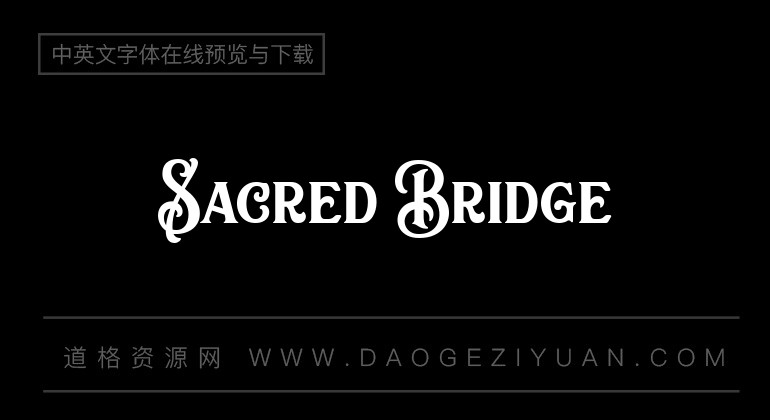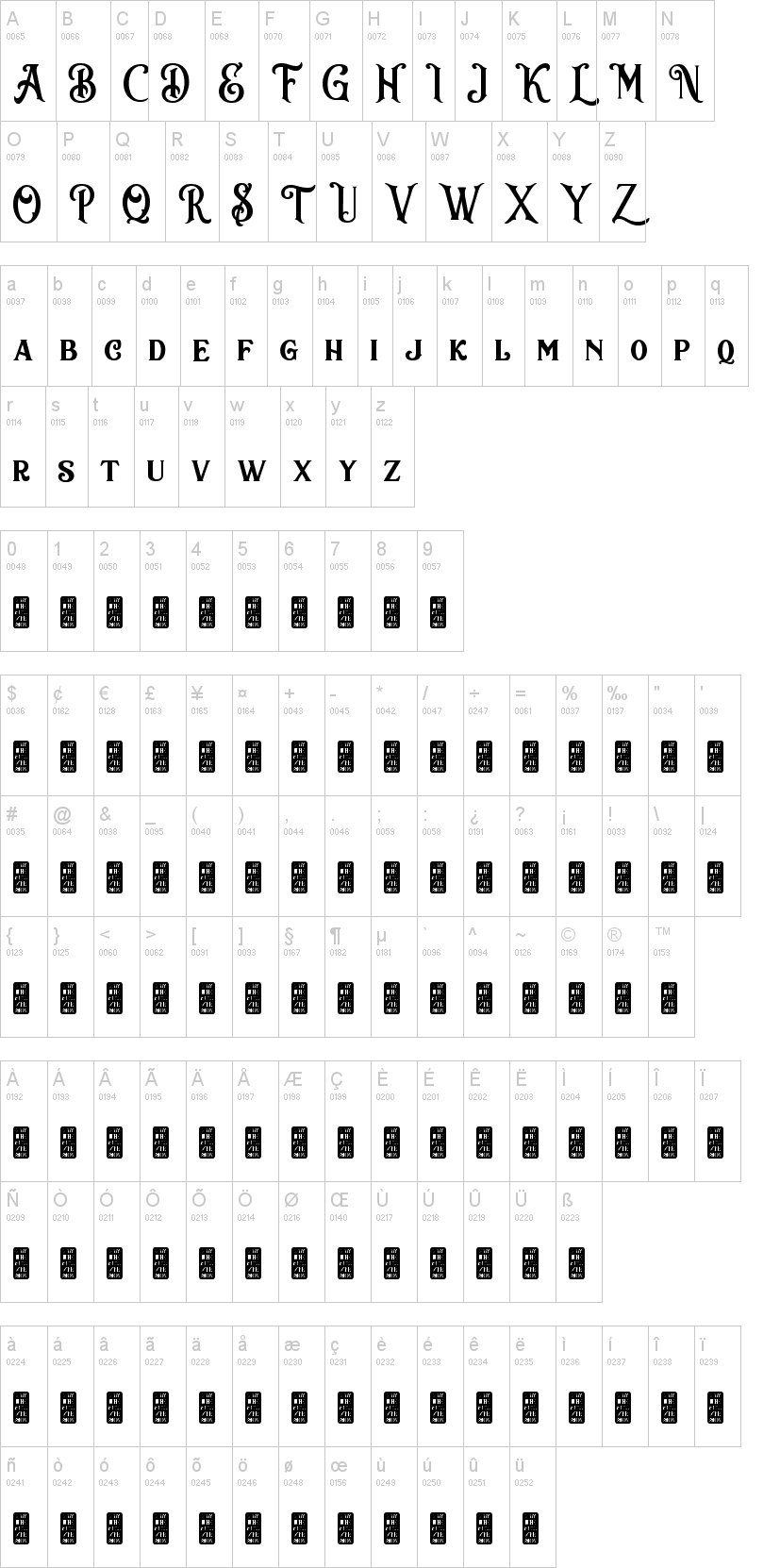
Sacred Bridge 是一款新兴的字体,它由两位设计师结合了传统的楷书字体和现代的设计风格设计而成。Sacred Bridge 的字形细腻,笔画流畅,拥有清晰的轮廓,让人一眼就能识别出来。它的字体结构简单,可以在各种尺寸的屏幕上清晰地显示出来,同时也具有良好的可读性和可访问性。Sacred Bridge 的字体非常适合用于多种应用,如网页、平面设计、印刷品等,可以为设计师带来更多的创意空间。内容介绍
Sacred Bridge是一款非常不错的手写艺术字体,具有很好的视觉感,适合于文化类的宣传设计、商业类品牌的广告和产品包装设计以及个性化文字排版等较多场景。